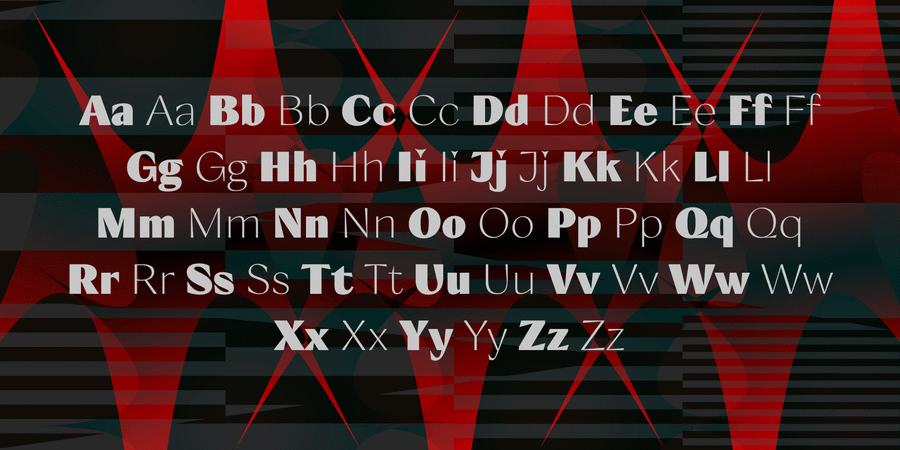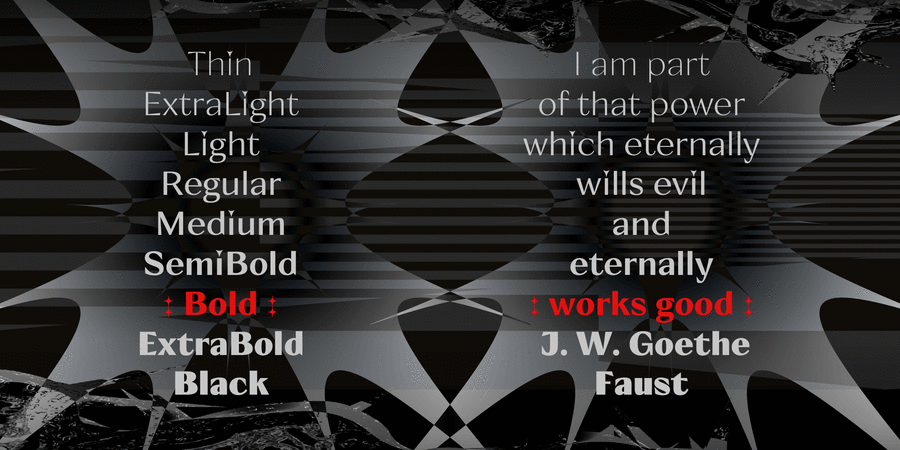
Deviless (10 шрифтів)
Deviless – це акцидентний шрифт із витонченими, гнучкими формами та диявольським характером. Яскрава харизма шрифту може стати родзинкою вашої айдентики, дизайну упакування або постеру. Шрифт має 9 накреслень – від тонкого до найжирнішого. Deviless має ще гостріші альтернативи, що містять жала. Це посилює характер і силу висловлювання, та додає виразного смаку будь-якому дизайну. Шрифт розробили Марія Вайнштейн і Кирило Ткачов у 2024 році.
Асоціації з сімейством шрифтів DevilessОсобистість і характер гарнітури:
тонкий, худий, витончений, чистий, легкий, свіжий, модний, якісний, культурний, добірний, благородний, елітний, дорогий, розкішний, красивий, майстерний, знаменитий, оригінальний, багатий, сучасний, міський, прозорий, аристократичний, салонний, урочистий, дзвінкий, гострий, світський, сріблястий, ефектний, срібний, крихкий, ювелірний, виразний, характерний, пафосний, художній, сексуальний, колючий, блискучий, глянцевий, естетський, пристрасний, прекрасний, вишуканий, різкий, чіткий, ексцентричний, артистичний, естетичний, освічений, гармонійний, гордий, джентльменський, дорогоцінний, комільфо, гламурний, драматичний, сміливий, цікавий, помітний, яскравий, твердий, золотий, авторитетний, стійкий, претензійний, переконливий, сильний, впевнений, амбітний, кінематографічний, екстравагантний, гучний, нічний, експресивний, театральний, святковий, романтичний, привабливий, експериментальний
парфумерія, дієта, туалетна вода, шампунь, срібло, розкіш, люкс, вино, ресторан, комільфо, мода, краса, косметика, мистецтво, преміум, шоколад, прикраса, ювелір, коштовності, сервіровка, алкоголь, лікер, парфуми, бутік, Місто, дизайн, годинник, лосьйон, готель, кава, Трофей, нагорода, культура, художник, музика, опера, коньяк, чай, захід сонця, драма, карти, золото, діамант, скульптура, графіка, ілюстрація, сукня, кохання, романтика, цукерки, бар, інтер'єр, одяг, Модель, салон, туфлі, каблук, фарби, кіно, театр, перукарня, кафе, взуття, костюм, концерт, вечір, розваги Гарнітура має ознаки стилів: